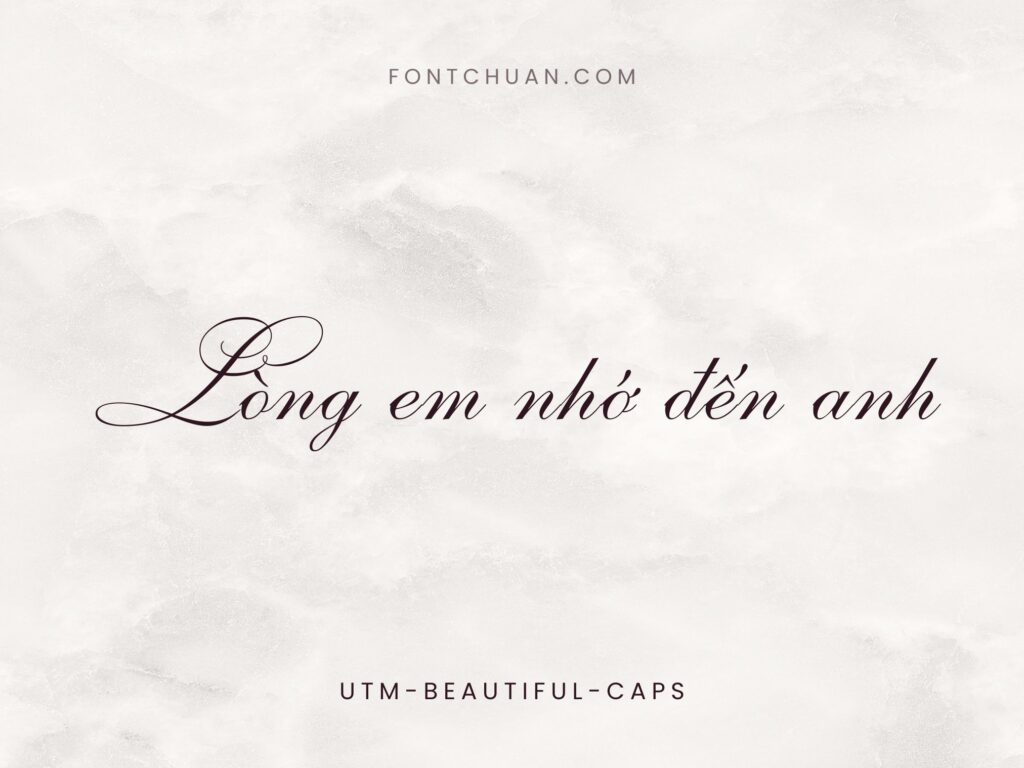
Font UTM Beautiful Caps Việt Hóa
UTM Beautiful Caps là phiên bản Việt hóa của font chữ Beautiful Caps, một kiểu chữ viết hoa trang trí với phong cách cổ điển, mang đậm phong cách Font Vintage và tinh tế. Font này nổi bật với các ký tự viết hoa được thiết kế tỉ mỉ, mang đến vẻ đẹp sang trọng và nghệ thuật cho các dự án thiết kế. Phiên bản Việt hóa đã được thực hiện, hỗ trợ đầy đủ tiếng Việt cùng hơn 100 ngôn ngữ khác. Đây là một trong những font được cộng đồng thiết kế sưu tầm và chọn lọc nhằm đáp ứng nhu cầu đa dạng trong thiết kế.
UTM Beautiful Caps có cấu trúc chữ với các nét uốn lượn mềm mại và chi tiết tinh xảo, tạo nên sự nổi bật và thu hút. Font này phù hợp cho các ứng dụng như thiết kế thiệp mời, tiêu đề, logo và các ấn phẩm in ấn yêu cầu sự trang trọng và nghệ thuật. Các ngành nghề như quảng cáo, giáo dục, công nghệ và bất động sản có thể tận dụng UTM Beautiful Caps để tạo điểm nhấn độc đáo trong thiết kế.